很少有品牌会量身定做一整套中文字体。
和做西文字体相比,那会是个超级辛苦的工作。一套英文字库包含标点和特殊符号,通常在 230 个字左右。但是一放到中文字体,这个工作量就会膨胀到六七千字。
2020 年 5 月 8 日,可口可乐放出了一套稍微有点“复古”的“在乎体”,供个人非商用和公益使用,你还能到天猫上定制刻字易拉罐。这个字库包含了完整的 6769 个汉字与 976 个字符。
△ 可口可乐在乎体。图片来源 | 方正字库
当天是可口可乐 134 岁的生日,也是 1979 年以来回归中国内地市场的第 41 个年头——因中美关系恶化,它曾撤离了一段时间。
你可能会从“在乎体”上看出熟悉的迹象,它脱胎自可口可乐的老商标。此前,可口可乐曾联合汉字文化传播机构好字在,在北京中粮广场办了一场特展。好字在为此制作了约 1200 多个活动用字,其中包含可口可乐宣传语,并请多名艺术家以“在乎”为主题创作。
△ 可口可乐老商标。图片来源 | 可口可乐中国
△ 2019 年 10 月 24 日,可口可乐“中国字·在乎体“文字特展在北京中粮广场中庭艺术空间开幕。图为艺术装置《穿越时空的对话》,艺术家为王丽华。她从唐朝诗人李白的《静夜思》的诗句中获得灵感,剪出并串联起 32600 多个字,“在乎体”融入其中。图片来源 | 可口可乐中国
方正字库看到机会,2019 年 11 月与可口可乐谈下合作。此前,可口可乐中国的广告用字最常使用的字体就是方正正黑系列,但推出定制字体还是第一次。
为品牌做一套中文字库,大致需要三个阶段。首先,字体公司的创意总监或主设计师和品牌方交流,将需求转译为视觉创意。然后,几名主力设计师设计出 50 多个常用字,尤其是企业常用字,供品牌方选择。这是个反复磨合的过程。
“让客户测试、直观感受这款字体。好比衣服要穿上身试。”在乎体的主设计师仇寅说。他也是一名硬笔书法家,现任北京北大方正电子有限公司字库业务部字体设计总监。
基于定下的字形,字库设计才进入最终阶段:规模化制作。主设计师定下字体的设计规范,例如基础笔画和结构,再交给设计团队。项目从立项到完成,限时 6 个月,方正字库为此配置了 20 人的团队。
如果是英文字库,由于字符量相对可控,小作坊、个人设计师可能在一年内独立设计出一套字体。中文字体设计师林越解释说:“一位独立字体设计师最多只需要两个月就可以完成一套多种粗细、支持泛拉丁字母(如 ä,ø,ñ)的字体,卖 10 美元的价格,买家能够承受,设计师也能够被养活。”
中文字库的逻辑则完全不同。据中国国家标准总局发布的简体中文字符集(GB2312-80 标准)规定,一套字体需收录 6763 个汉字。
仇寅表示,设计中文字体如此规模的作业,难点在于控制字库内字与字的一致性,这依赖的是素养好、配合紧密的设计团队。
制作上千个字符时,设计师的挑战之一,在于如何让汉字风格一致却富有变化。如“口”的字形,作为“呆”“嗝”“噗呲”“器”的偏旁,需要分别“量身定做”。这一步可能需要 10 人以上看图找字。
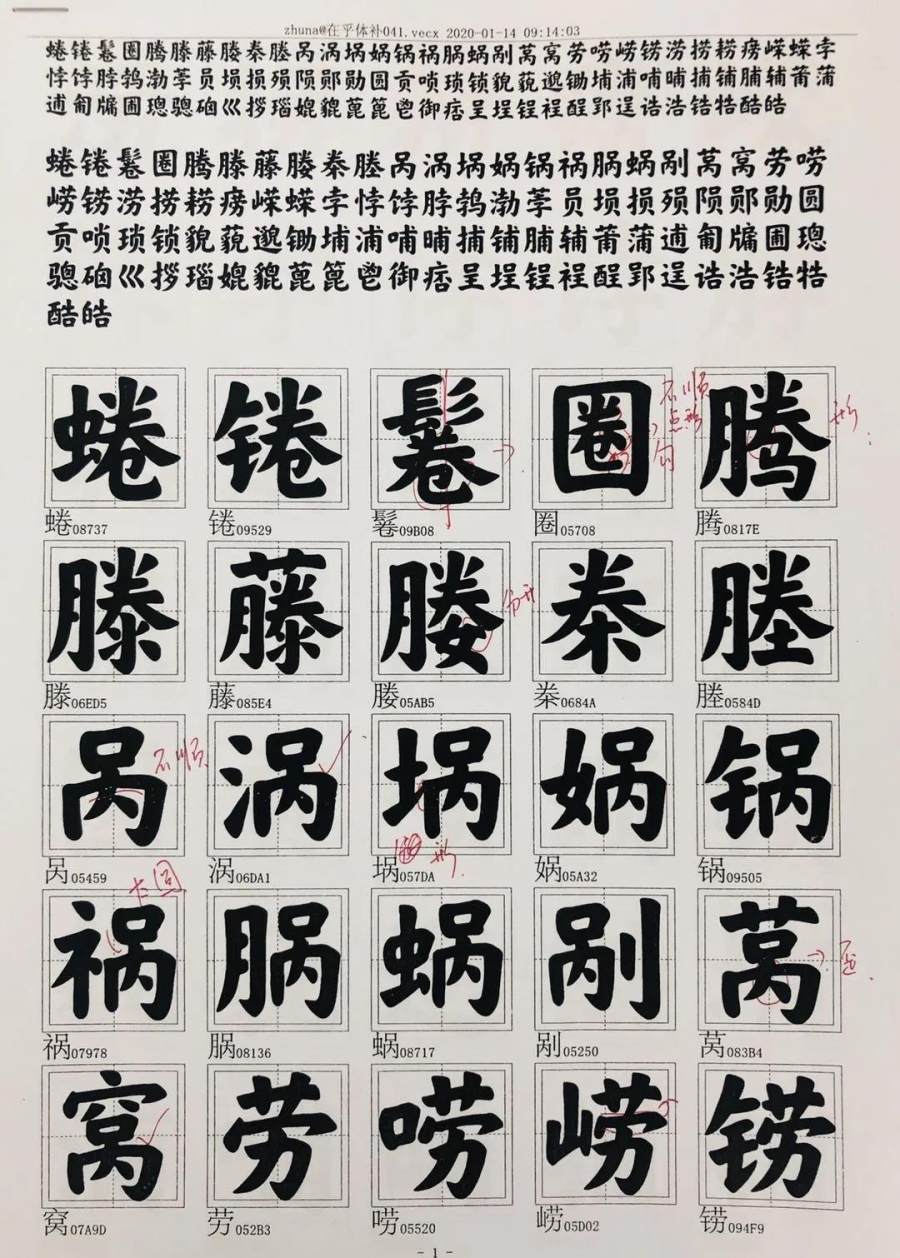
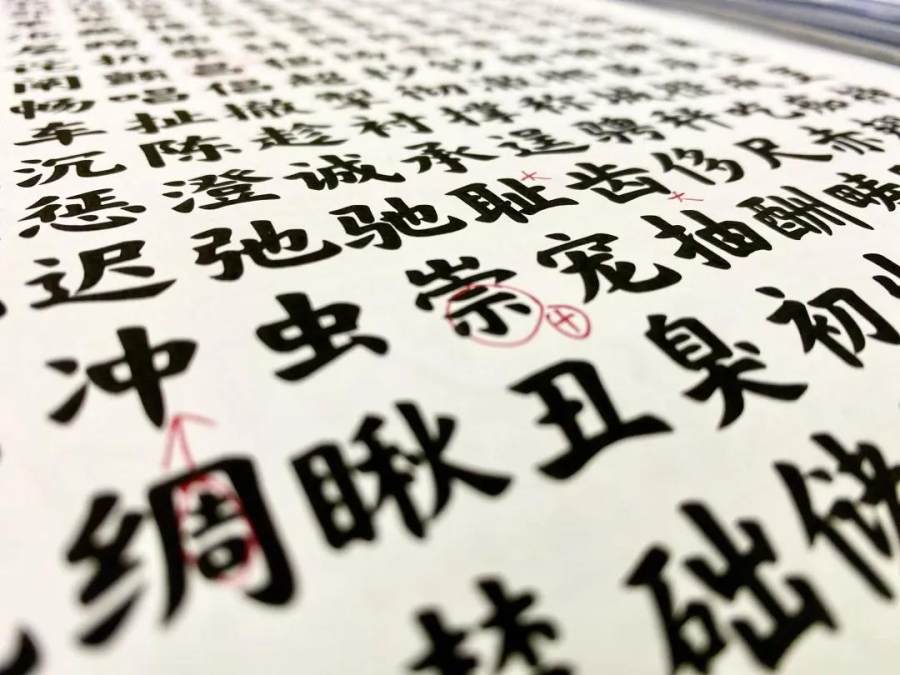
△ 在乎体设计过程中的校对稿。图片来源 | 方正字库
在林越看来,中文字库开发是件吃力不讨好的事。“中文字体能够上市的底线字数是 7000个左右。你每套字库卖 100 块,即使消费者可以接受,也回不了本,无异于免费。”据她估计,高质量的汉字,每人每天差不多能做 20 个——在另一些机构,这个速度可能会更慢。
另一方面,这也让品牌出资、字库开发的模式找到了空间。目前,在乎体由方正字库运营和处理商用授权——这也是方正首次尝试这种合作方式。但方正字库也表示,不便透露字体开发成本、所有权与销售分成等情况。
字体公司的主要营收来源仍是授权。方正字库向未来预想图证实,中国市场的商业定制刚刚起步,业务占比较小。方正也提供企业、嵌入式应用、网页云字库等服务,还与政府信息库合作。
但无论是哪一个领域,中文庞大的字体开发成本,既限制了字体公司的利润空间,也夺走了很多品牌选用字体做营销的勇气。目前,在全球范围内,苹果、微软、索尼、H&M 等公司或品牌都定制过品牌字体。在中国,只有阿里巴巴、腾讯、京东等大公司尝试过品牌字体定制。
△ 阿里巴巴的定制字体囊括了当前全球大部分的货币符号。图片来源 | 淘宝设计
从现阶段看,做中文字体开发并不会给定制字体的品牌带来太多直接收入。可口可乐中国从这桩合作当中更多获得声誉传播——“在乎体”既能反映公司的历史文化,又能体现对中文市场的重视。
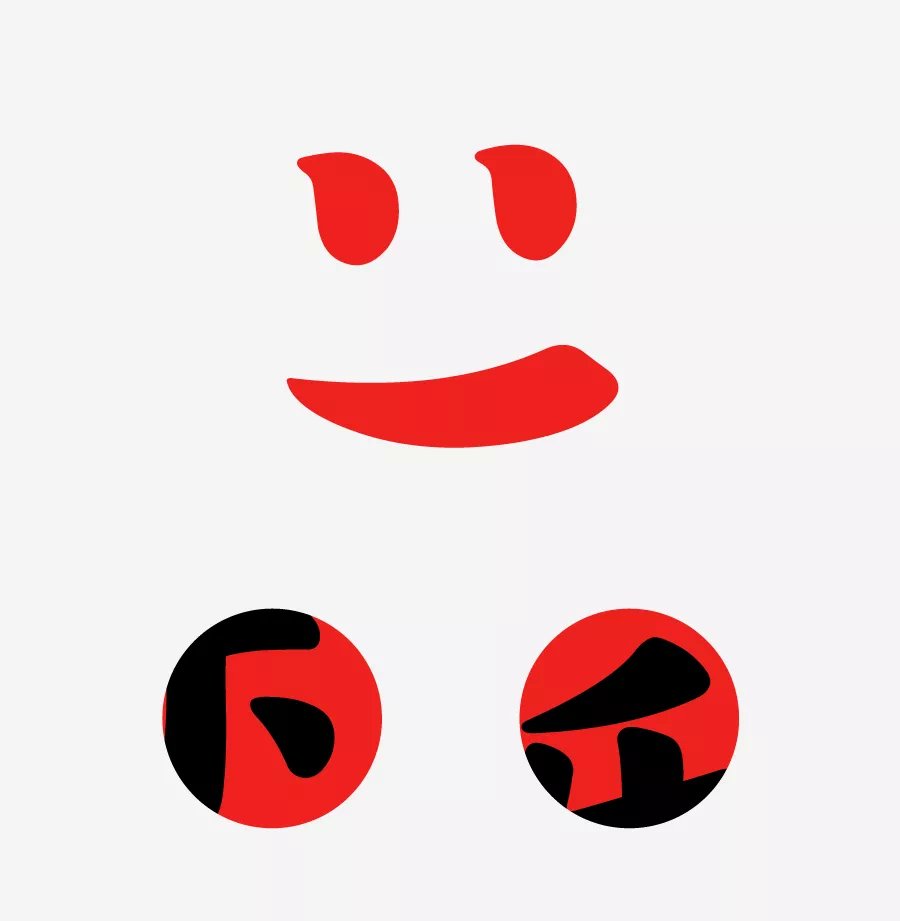
△ 在乎体收录了可口可乐的标志性在乎笑脸,在输入法中输入“:)”可以直接打出来。图片来源 | 方正字库
“我们希望这套一方面载有可口可乐和中国消费者共同回忆、一方面对‘在乎’有理解和诠释的字体,能够为大家在数字时代提供一个有人情味的书写选择。”可口可乐中国回复未来预想图说。
负责这个项目的仇寅也为这套设计加上了他的解读:“字体是文字的衣裳,学中国文化要从学文字开始……这套字体需要展现圆融、从容的力量感,要肥而不腻。”
在乎体属于楷体,主要具有欧体和颜体的特点:欧体挺拔,拐角硬挺,颜体则宽厚粗壮,有水的流动性,这能化解欧体的尖锐感,同时不容易过于饱满。
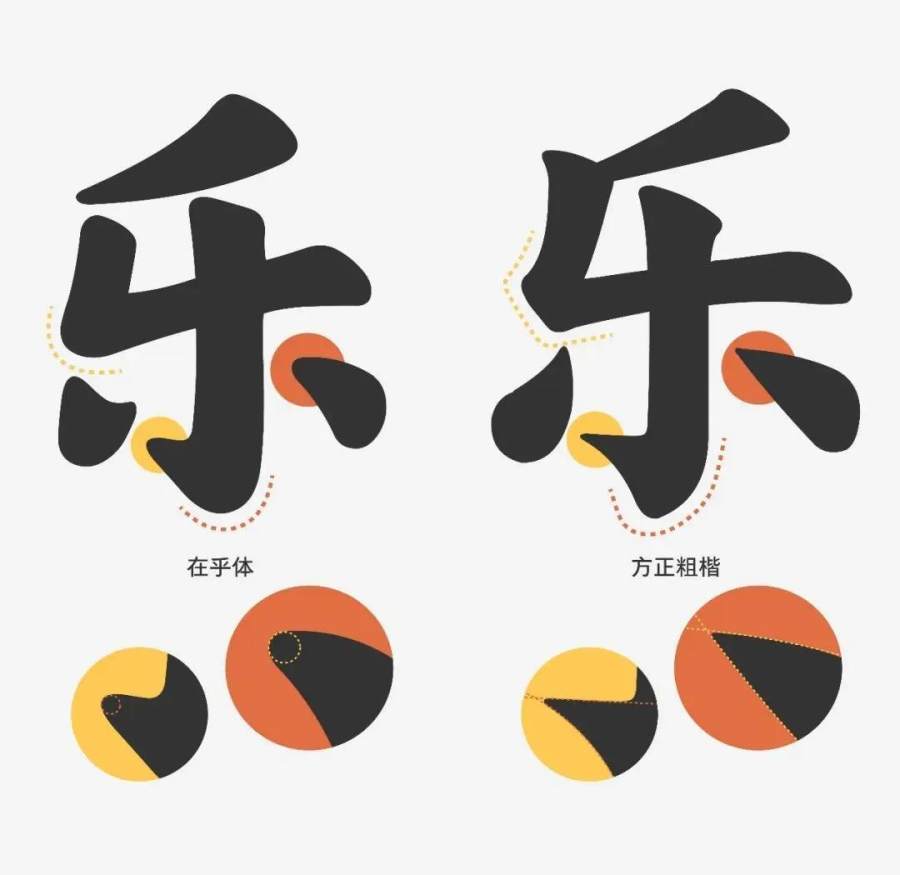
△ 相比方正粗楷,在乎体的笔画更加饱满、浑厚。图片来源 | 可口可乐中国
并非所有品牌定制字体都需要强烈的个性。按照开发用途区分,字体可以大致分为“展示字”(display)和“文本字”(text)。在乎体属于“展示字”范畴,目的在于让人记住。“文本字”更重视可读性,要方便使用——印刷物上常见的黑体就属于这一类。
开发“文本字”的时候,规模较大的字体公司更有优势,它们拥有字形结构、笔画细节等领域的详尽数据,也能配置人数更多的设计师队伍。而“展示字”包含美术字和书法字,相对而言,对数据积累和字体排印知识的要求要少一些。
即便跨越开发困难、交付字库之后,字体设计公司的工作也没有结束,字库需要花精力维护。数字时代,字体是一个不断更新的服务。方正复查在乎体时,发现仍无法完整输出《心经》,所以需要修补上缺漏的单字,为用户提供字体新版本。
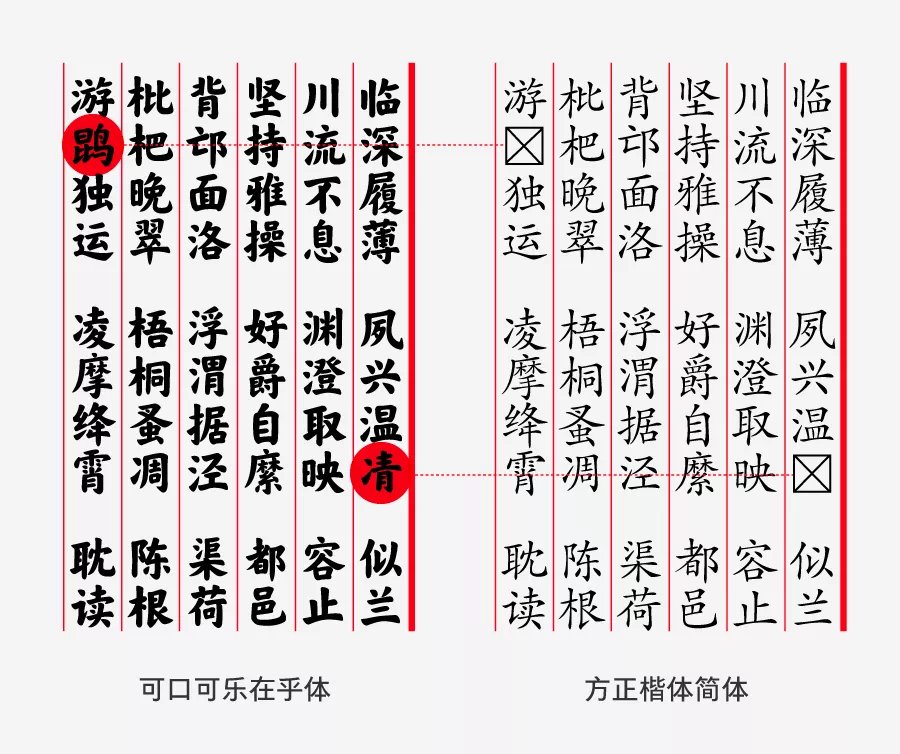
△ 在乎体是根据 GB2312-80 字符集设计制作的,但特别收录了 GBK 字符集中“凊”“鹍”等汉字。因此,相比普通的方正楷体,使用在乎体可以打出《千字文》的全文。图片来源 | 方正字库
字体的设计,首先是可用,而汉字的“可用”范畴,也在随着网络文化的发展而拓宽边界。像原意为明亮的“囧(jiong)”,梅的异体字“槑(mei)”,都不常用,但近几年,人们开始发掘生僻字,现有的 GB2312-80 简体字标准已经不能应付需求。因此,方正字库在新编的 748 编码标准中额外收录了这些字。
合体字则是汉字的另一种“玩法”。这些用两个或两个以上的单字拼成的字符,意义与原来的词语、词组完全相同。它源于民俗文化,历史可以追溯到汉朝民间用来“镇鬼魂”的画符,到了清代,人们也会在元宝、红纸上镌刻合体字的吉祥话。
仇寅告诉未来预想图,方正需要利用 OpenType 字体格式的特性来实现那些“不可能”的汉字。“比方说过年我们爱说‘招财进宝’‘吉祥如意’,用户在四个字最后加上不常用的百分号‘%’就能打出这个合字,表达逢年过节的温暖。”
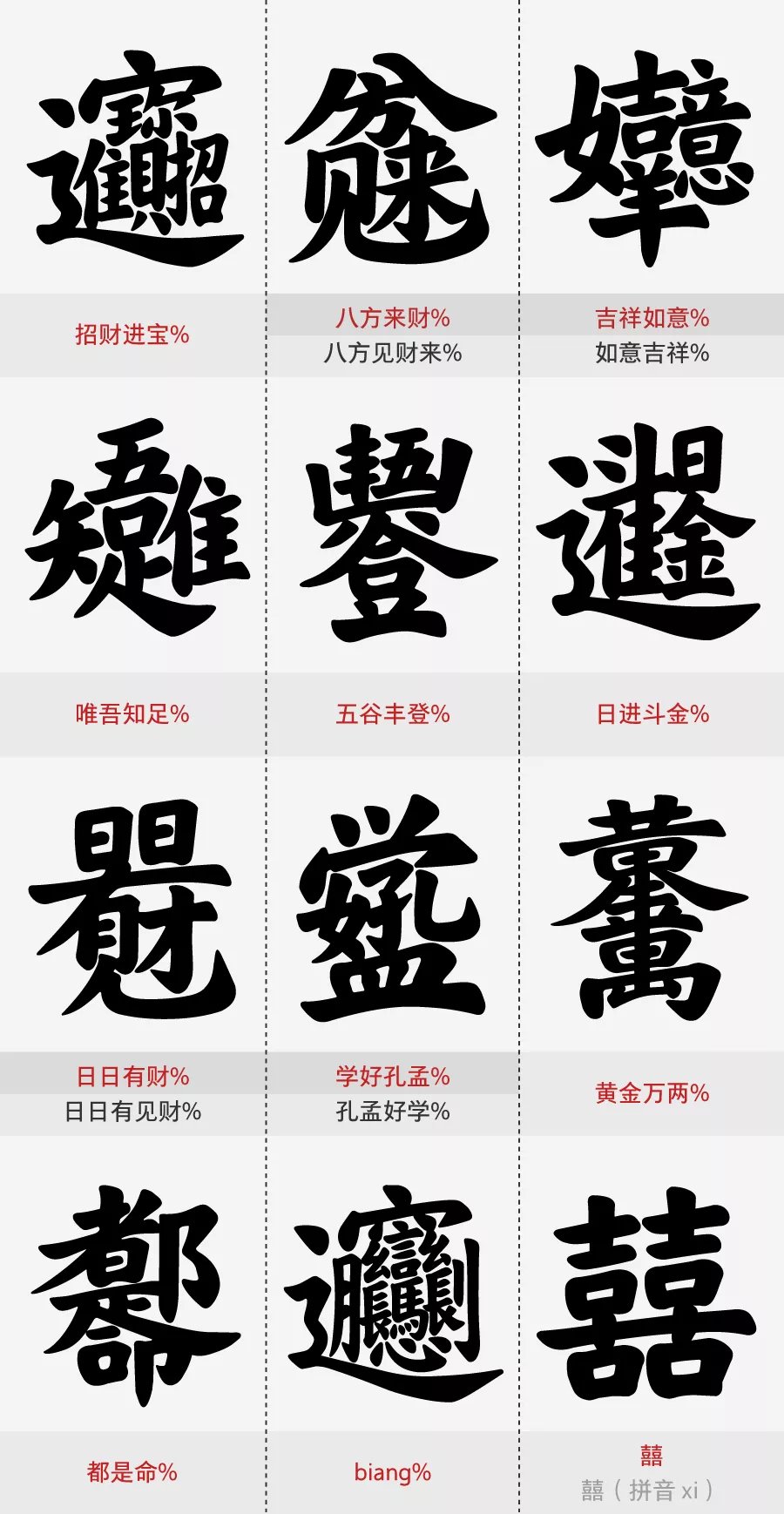
△可口可乐在乎体中的一些特殊字符,也是为了致敬中国传统文化。红色和灰色的小字是合体字在 Adobe 系列软件中的输入方法。图片来源 | 方正字库
数字时代也意味着更多新机会,更多字体设计和开发的新技术也可能带来更多用户体验上的变化。在小米向方正字库定制的字库中,小米兰亭 Pro 就是个三轴可变的字体——也就是说,字的宽(width)、高(height)、字重(weight)都能调节,可粗可细、可胖可瘦。设计师设置了 10 个字重(相对于字高度的笔画粗细程度),确保调整过参数的字依然易读。用户可以根据自己的需求,调节系统界面字体的大小,系统会自动匹配字重。
△ 可变字体的中宫可变演示。中宫是书法中的一个常见的概念。在书法中,写楷书常参考的界格是“九宫格”,即把一个大方格等分成九个小方格,最中间的一格就是中宫。在字体设计中,中宫会影响字体的结构,进而影响字面的大小。图片来源 | 方正字库
方正字库业务副总经理黄学钧告诉未来预想图,他们认为可变字体是字体产业的新方向。结合更好的屏显支持,有可能带来革命性的应用。
OpenType 可变字体规范由微软、Adobe、苹果和谷歌于2016 年 9 月的 ATypI(国际文字设计协会)上联合发布,也是四家技术公司首次统一相关规范。一经宣布,可变字体成了字体行业的重点关注对象。
可变字体最便利的地方是节省储存空间,能将一套字体的多种变体整合成单个文件。根据美国蒙纳字体公司的试验,一款整合 48 种变体的西文可变字体只占 55 KB,能节省 88%的文件大小。而中文字结构复杂、细节讲究多,设计师需要在控制字体的可变轴上精修中间状态的母版(master),这些是字体变化程度的锚点。一套上百兆的中文可变字体,可能有多个母版,这让成品用起来和常规字库差别不大。林越指出,这也是可变字体目前的争议。
中国消费者也逐渐开始感受到字体识别的力量。上一次让更多中国普通消费者意识到品牌与字体的关系,还是在 2017 年腾讯推出企业字体的时候。那时,人们好奇的是,为什么这家中国大公司要“花大钱做这件事”。显然,那一阵的新闻热潮达到了传播效果。
这些“行业中的热潮”可能会在某种程度上改变人们对美的认知。黄学钧和仇寅也认为,字体的个性与美观的重要性,近十年来,已经得到来自品牌、企业和社会更广泛的认可。
△ 方正的字库形象墙。图片来源 | 方正字库
但在中国搜字体,字库的非法使用一直是个问题。方正字库因字体被复刻、非法商用打了大量官司,小型字库公司、个人设计师大多忍气吞声。据《南方周末》报道,2002 年至 2010年间,曾是亚洲最大字库公司的汉仪字库一直未能推出新字库,因为几乎没有客户主动支付使用费。
在版权保护更为严格的地区,字体的使用与规范要更加体面一些。美国蒙纳字体公司 2018 财年的收入为 2.467 亿美元,净利润为 1230 万美元。微软 Windows 系统内置的默认字体 Arial 就是它的代表作。这套系统如今在全球有超过 10 亿用户。
△ 常见的 Arial 字体。图片来源 | designworkplan.com
也许,随着中文用户的版权意识和用字习惯渐渐好转,越来越多热爱汉字的人能靠字体设计谋生。但仇寅也提及,字体设计是国内设计教育的边缘——相比国外美术学校,中国还缺乏完善的课程体系与实践。
问题可能还是集中在中文字库庞大的创作成本上,它是否能带来足够显著的营收或传播效益,既影响着设计人才的流动方向,也影响着各品牌未来的营销预算。